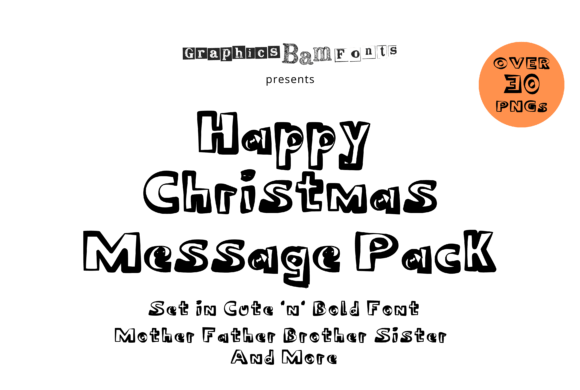
35 Happy Christmas in Cute 'n' Bold Font
Пошук відповідних елементів дизайну може бути складним, але 35 Happy Christmas in Cute 'n' Bold Font пропонує виняткову колекцію, яка миттєво покращить вашу роботу.
Незалежно від того, чи створюєте ви продукти POD (друк на вимогу), весільні запрошення або графіку для соціальних мереж, 35 Happy Christmas in Cute 'n' Bold Font стане ідеальним вибором.